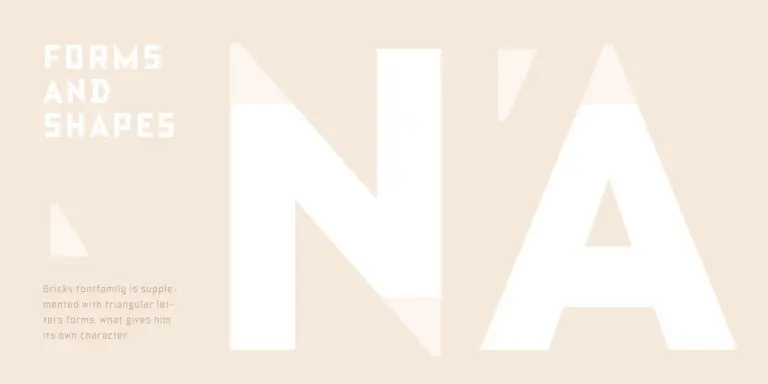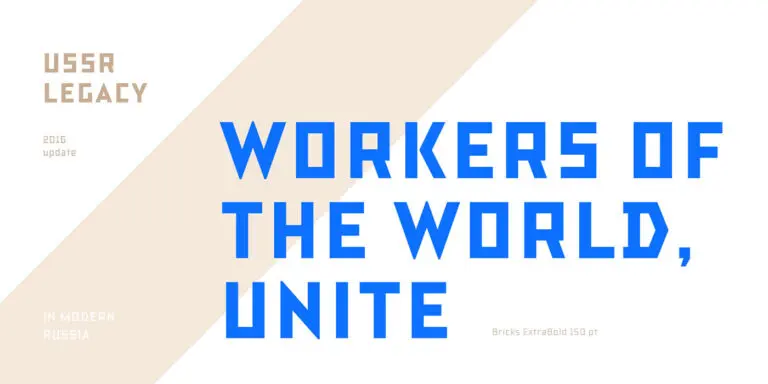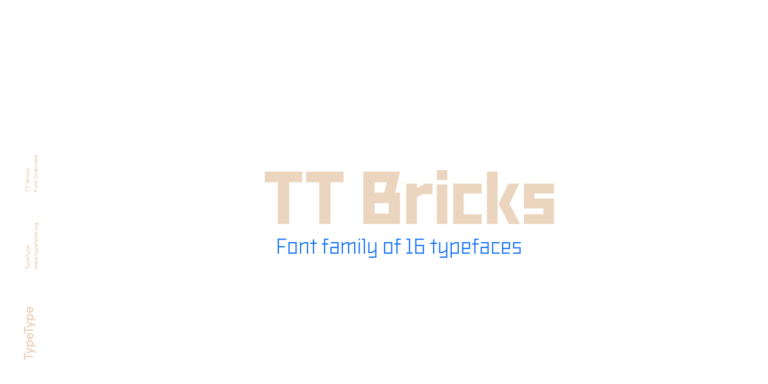
TT Commons™ Pro es una versión completamente rediseñada de la consolidada familia tipográfica clásica TT Commons.
¡Seguimos ampliando la línea del principal bestseller del estudio: TT Norms® Pro!
TT Supermolot Neue es una reinterpretación rediseñada, ampliada y notablemente mejorada de la popular familia tipográfica.
TT Rationalist es una tipografía slab serif funcional y neutral.
TT Turns es una impactante sans serif geométrica con elementos expresivos. Esta versátil tipografía funciona excepcionalmente bien en textos corridos y, en tamaños grandes, adquiere un marcado carácter display.
TT Modernoir es una display sans serif con proporciones dinámicas. Las líneas fluidas y las delicadas formas Art Nouveau se combinan perfectamente con el flujo rítmico y la libertad improvisadora del jazz.
TT Firs Neue es una reinterpretación contemporánea de la clásica sans serif TT Firs.
TT Biersal es una display sans serif con un carácter libre, juguetón y aventurero. El concepto de esta fuente nació a partir de un cartel alemán de principios de los años 30.
TT Travels Next es una moderna y muy actual sans serif display de gran anchura, diseñada para utilizarse tanto en medios impresos como digitales.
TT Octosquares es una versión renovada, revisada, ampliada y significativamente mejorada de nuestra primera tipografía comercial TT Squares y de su versión estrecha.
TT Carvist —peculiar, divertida y valiente— capta la atención de forma excelente.
Hemos lanzado una fuente completamente nueva. Descubre TT Firs Text: una sans serif geométrica con carácter nórdico.
Una familia tipográfica tecnológica para diseño de videojuegos.
TT Autonomous es una moderna sans serif techno con amplias proporciones angulares.
TT Berlinerins es una grotesca inspirada en los tipos de madera utilizados en carteles durante el primer tercio del siglo XX y representa el componente histórico de Berlín.
TT Bricks es la respuesta para los amantes de la cultura soviética. Hemos intentado retroceder cien años y reinterpretar la era del constructivismo.